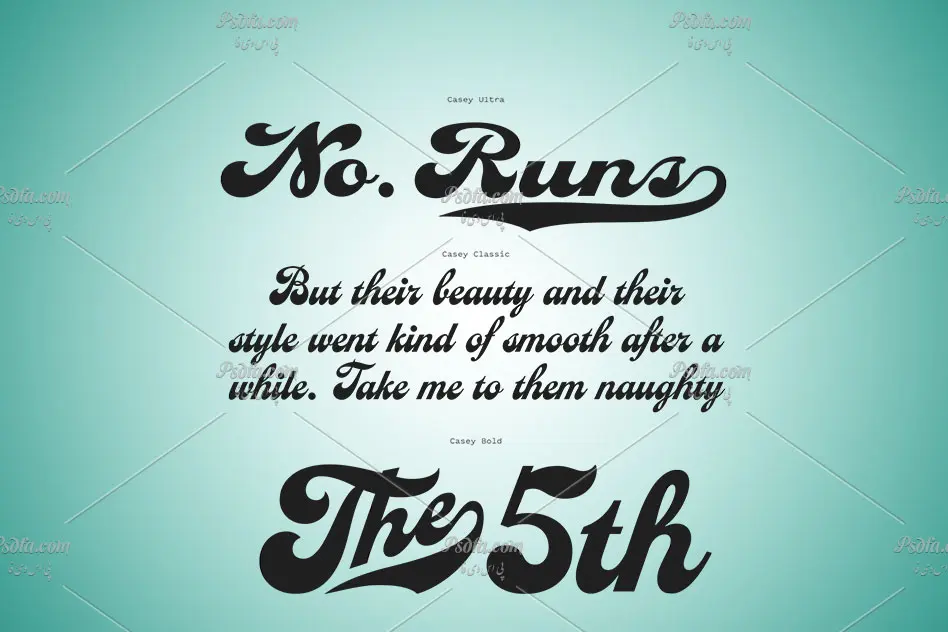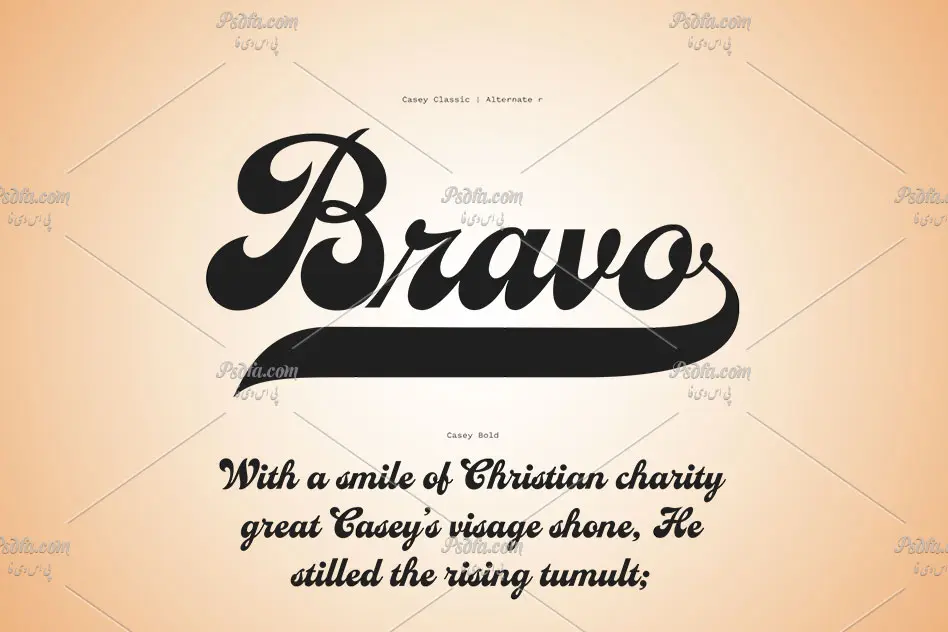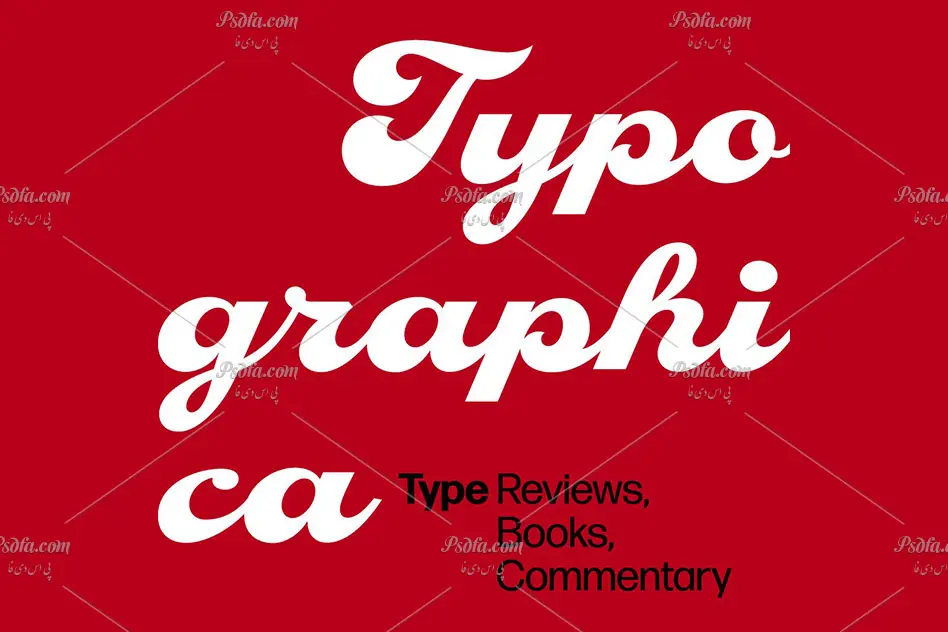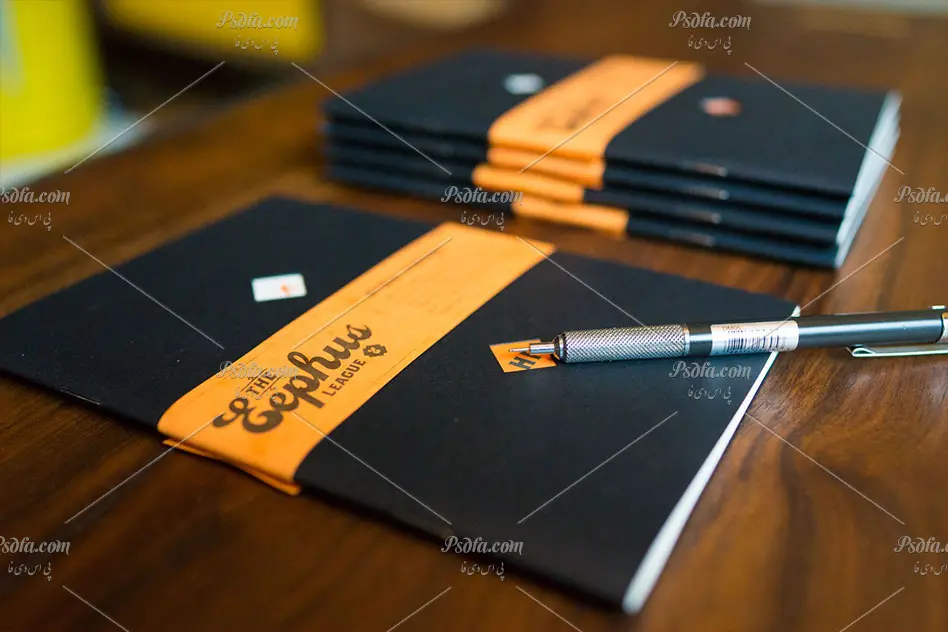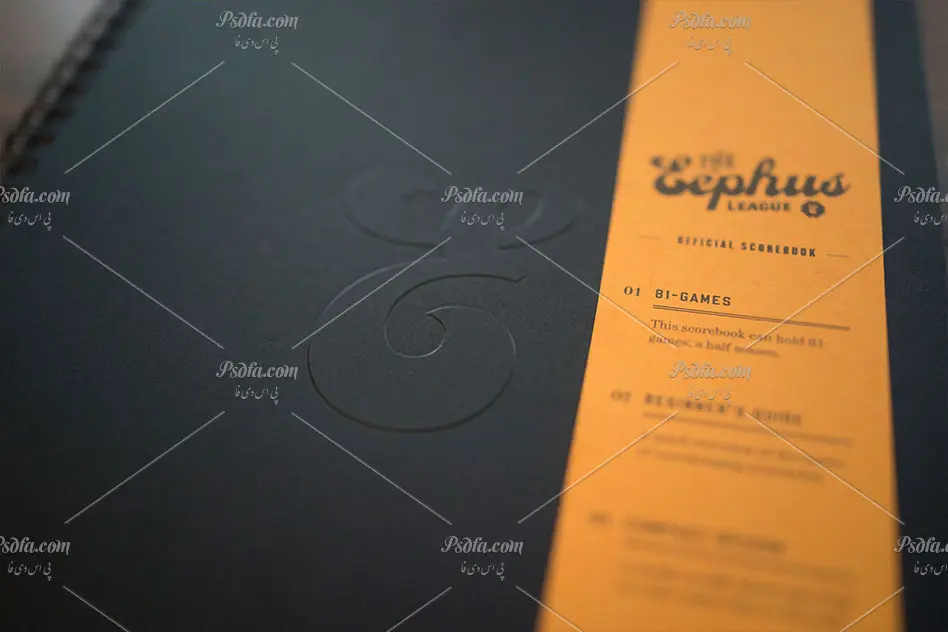
فونت انگلیسی Casey مناسب برای طراحی و گرافیک
در این مطلب برای شما دوستان و طراحان عزیز فونت انگلیسی Casey را در سایت قرار داده ایم که از آن می توانید در طرح های خود به خصوص طراحی انواع پوستر بهره مند شوید. این فونت انگلیسی فوق العاده زیبا در سه سبک و حالت BoldClassic و Ultra طراحی شده است که هر کدام ویژگی های خاص خود را دارد. همچنین فرمت این فونت otf است که پس از نصب این فونت در سیستم خود قادر به استفاده از آن در تمام نرم افزارهای گرافیکی و ویرایشگر متن از جمله نرم افزار محبوب فتوشاپ ، مجموعه نرم افزار آفیس و … می باشید. اگر از دسته طراحان و گرافیستان کارهای هنری و یا طراح انواع پوستر هستید به شما پیشنهاد می کنیم این فونت زیبا را از دست ندهید و از آن در پروژه های خود استفاده کنید. پیش نمایش این فونت را می توانید در تصویر بالا و یا گالری تصاویری زیر مشاهده فرمائید.
• کیفیت بالای فونت
• دارای سه سبک Bold , Classic و Ultra